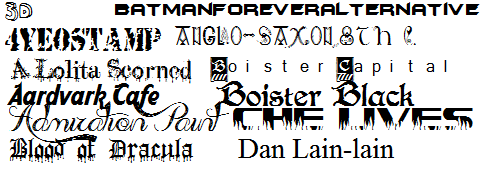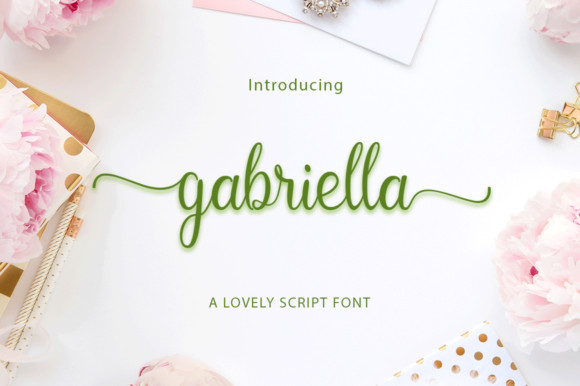
Dari semua jenis font saya sudah memilah yang terbaik untuk sobat.
Font keren untuk banner.
Ada banyak font keren dari berbagai desainer font di seluruh dunia yang bisa sobat miliki tanpa bayar sedikit pun alias gratis.
Memang banyak sebuah font yang dibutuhkan dengan tergantung tema yang akan dibuat semisal untuk membuat undangan logo atau lainnya.
Download font keren untuk desain grafis logo poster dan banner pada kesempatan kali ini saya akan berbagi sekumpulan font latin keren yang memang sangat direkomendasikan bagi anda seorang desainer.
Font yang ciri khasnya memiliki bentuk huruf o yang seperti tengkorak.
Itulah 15 jenis font terbaik untuk desain grafis yang bisa kamu unduh download secara gratis.
Mulai dari kategori font graffiti font tulisan tangan hand writing hinggan font untuk tanda tangan digital lengkap dengan previewnya.
Font pilihan terbaik untuk desain grafis gratispada artikel kali ini saya akan mengupdate tentang font font terbaik dan gratis untuk anda.
Font fot ini sangat berguna untuk keperluan design grafis seperti membuat logo banner text art dll juga untuk keperluan mendesign sebuah web.
Disini saya kumpulkan beberapa yang telah saya pilih dari berbagai sumber yang sekiranya menurut saya bagus untuk melengkapi desain kita.
Terdapat banyak kumpulan font keren gratis yang bisa anda coba untuk mempercantik desain anda.
Font poster film suicide squad adalah font ini.
Setiap saya mendesain yang membutuhkan banyak variasi jenis font agar produk dihasilkan tidak monoton.
Seperti untuk desain cover buku proyek photoshop website kaos mockup gelas logo cover majalah layout buku dan desain lainnya.
Apalagi posternya tentang hal yang menegangkan atau peringatan.
Bisa dijadikan perpaduan baru untuk desain poster sobat.
Bagi siapa saja yang mencintai dunia desain pasti mereka juga berburu font font dalam membangun desain.
Ada font elegan font tipis font tulisan tangan dan lebih masih banyak lagi.